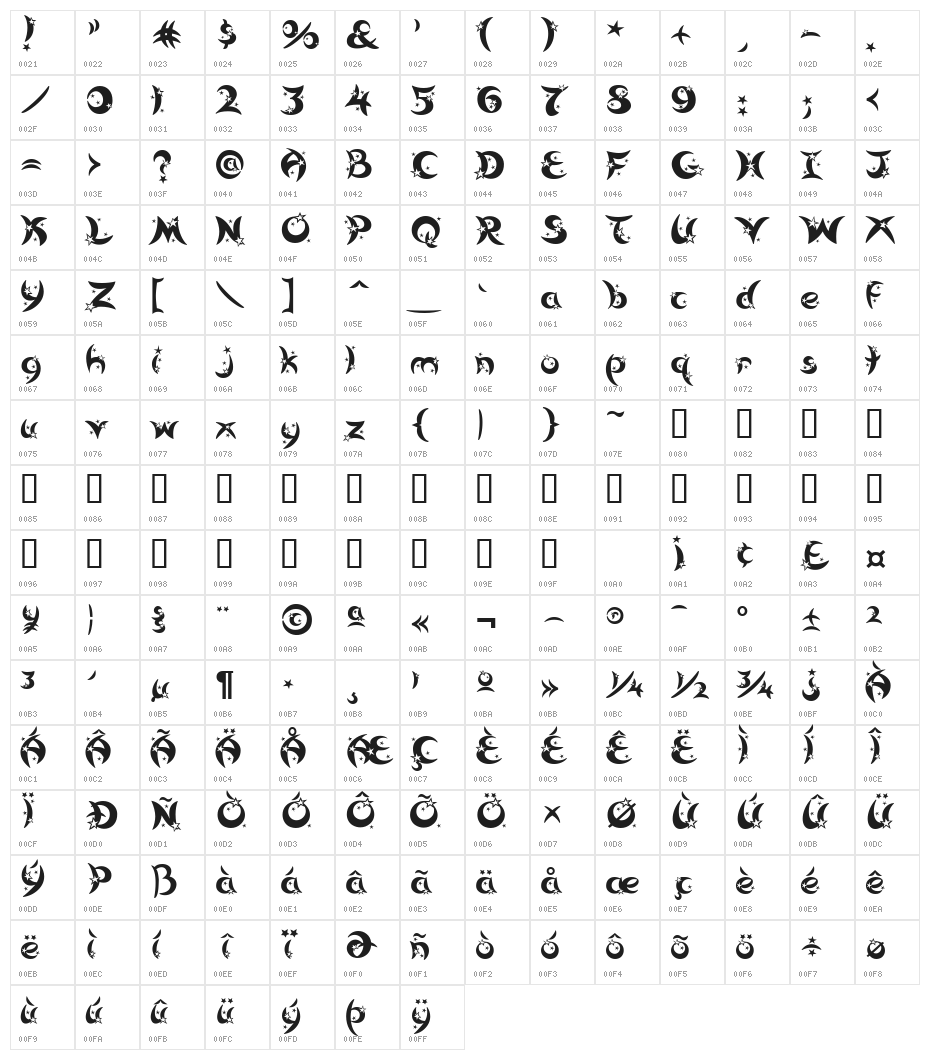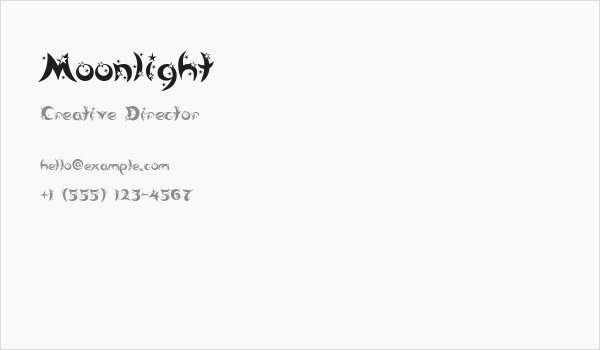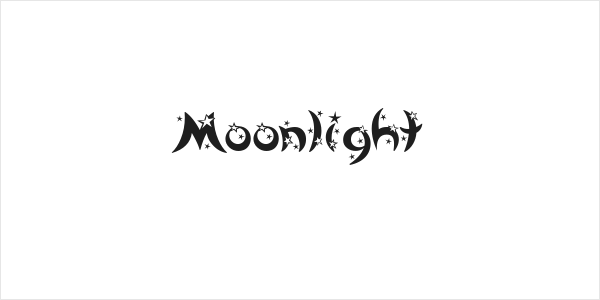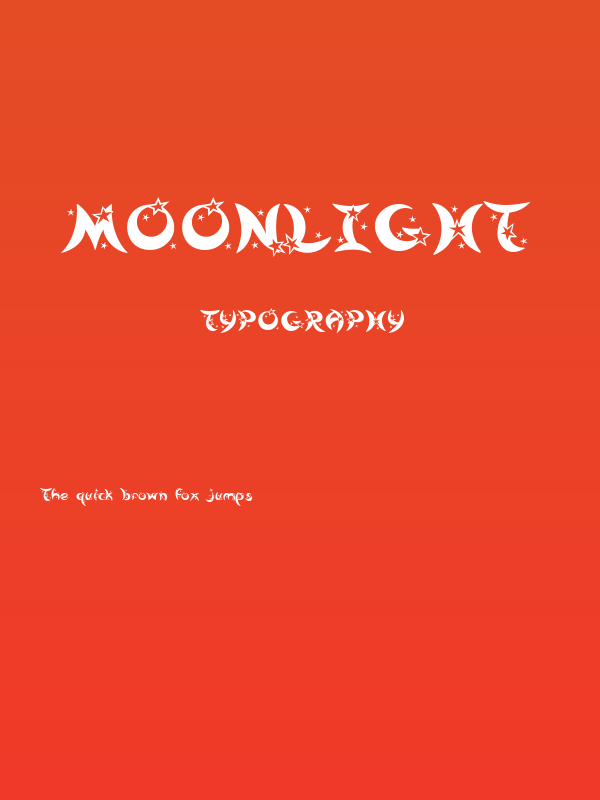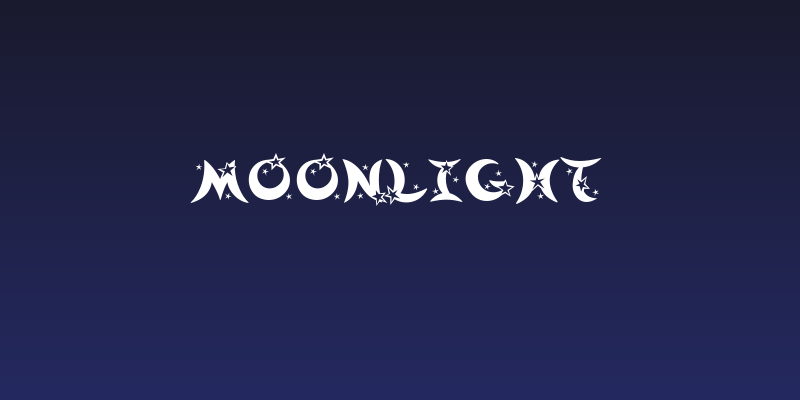
Moonlight Font
| Vorgeschlagene Projekte | Ideal for children's book covers, fantasy-themed posters, party invitations, or any project needing a magical, night-time aesthetic. |